Шрифты и их построение
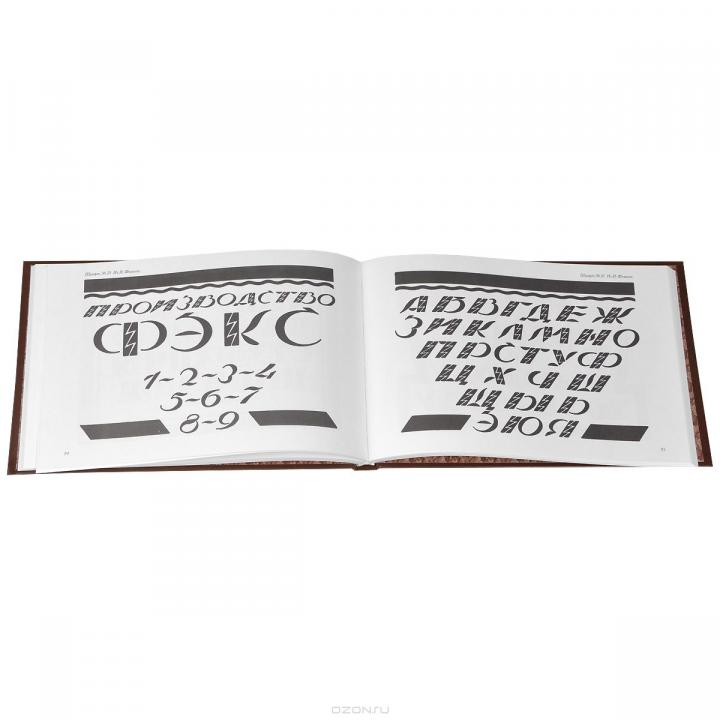
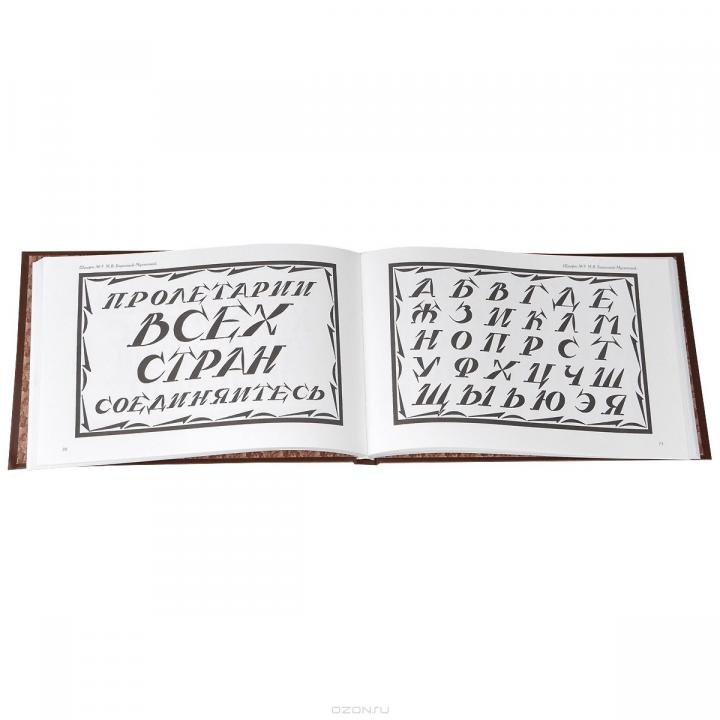
Настоящее издание является воспроизведением книги выпущенной в 1927 году в Ленинграде. Этот сборник дает материал по вопросу о писаном шрифте и методах его построения. Задачей альбома является дать живой материал о шрифте и творческом его применении и развитии. В нем собраны различные (орнаментированные, каллиграфические, титульные, брусковые, рубленые и др.) шрифты, созданные ведущими графиками Ленинграда.
Книга представляет интерес для учащихся и студентов художественных учебных заведений а также для всех, кто интересуется шрифтовой графикой.